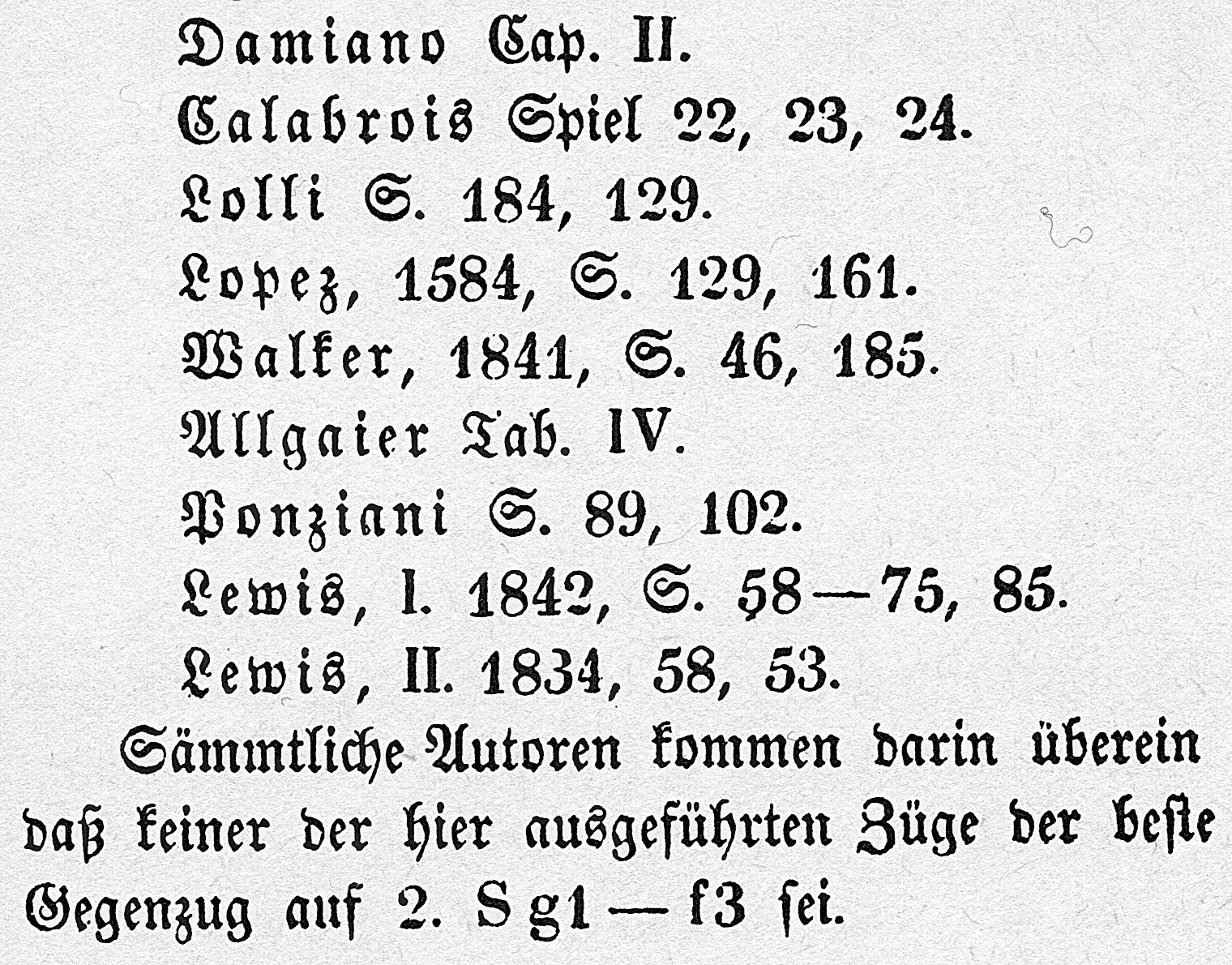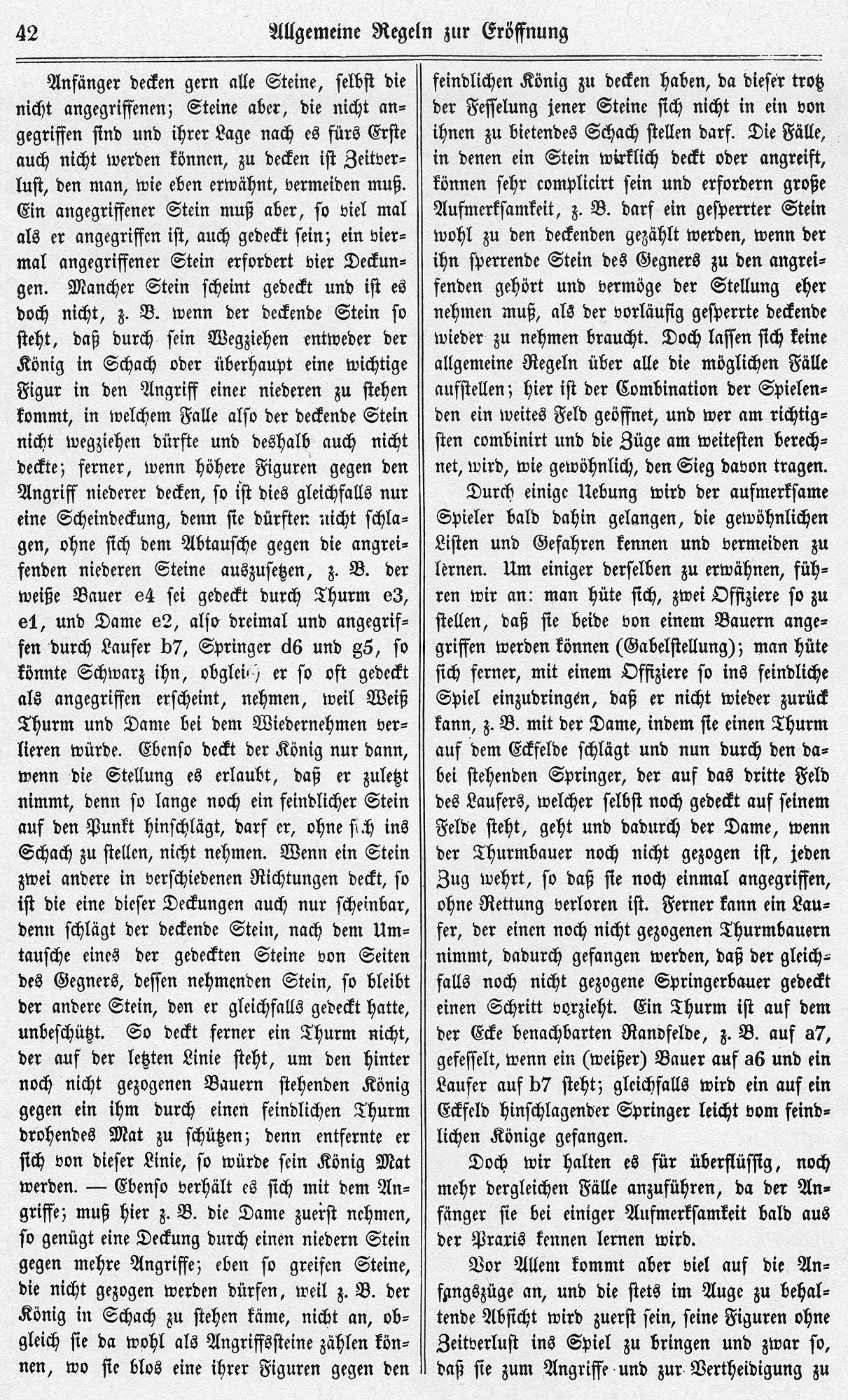
Schriftmusterbuch/-auskunft von Bilguer gesucht
Ich habe ein Buch von 1843 (der sogenannte "Bilguer", nach dem Erstverfasser), welches in Berlin bei Veit & Comp. gedruckt wurde. Mich würde interessieren, welche Fraktur von welcher Schriftgießerei hier zum Einsatz kommt. Die Ziffern sind sehr charakteristisch (z. B. die Eins und die Zwei). Beziehungsweise, ob es passend zur Zeit Schriftmusterbücher gibt. Ich habe etliche Frakturschriften verglichen, aber nichts annähernd passendes gefunden.